在各种工作软件里也好阅读的书籍也好应用的最多的还是“宋体字”。宋体字有着悠久的历史文化、字体风格简约大方,字形清晰易于 字体识别。随着时代审美的变换和更多的字体呈现需求,宋体字也在不断的演变创新,衍生出了多种新的风格诠释,下面就为大家推荐几款超好用的代表性宋体字吧。
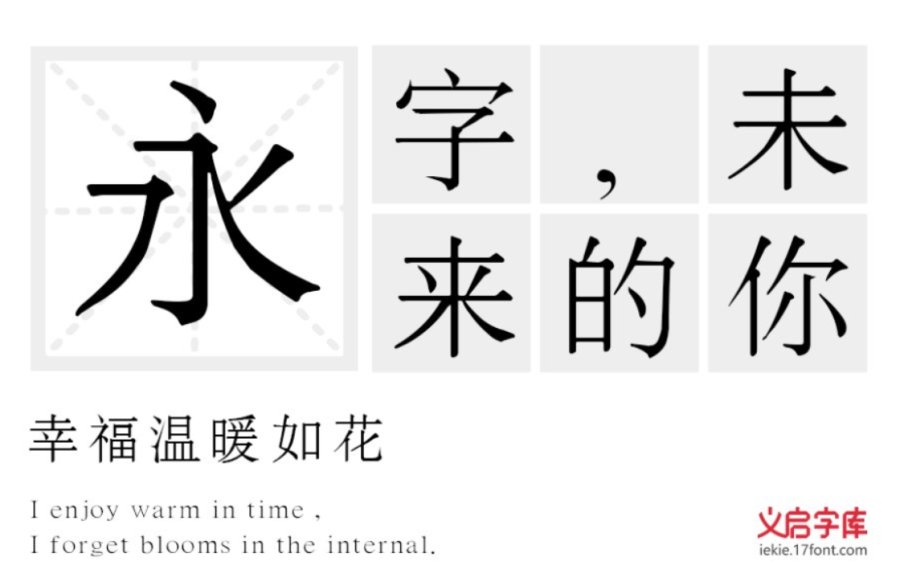
义启新宋体:这款新宋体在设计上延续了传统宋体适合印刷的风格特征,但是大大改善了在电子屏幕显示上的弊端,在比笔画上做出了细致的整改,保持比例平衡,笔画横细竖粗,字形更加清晰,适用于游戏、logo、广告、印刷等多种领域。
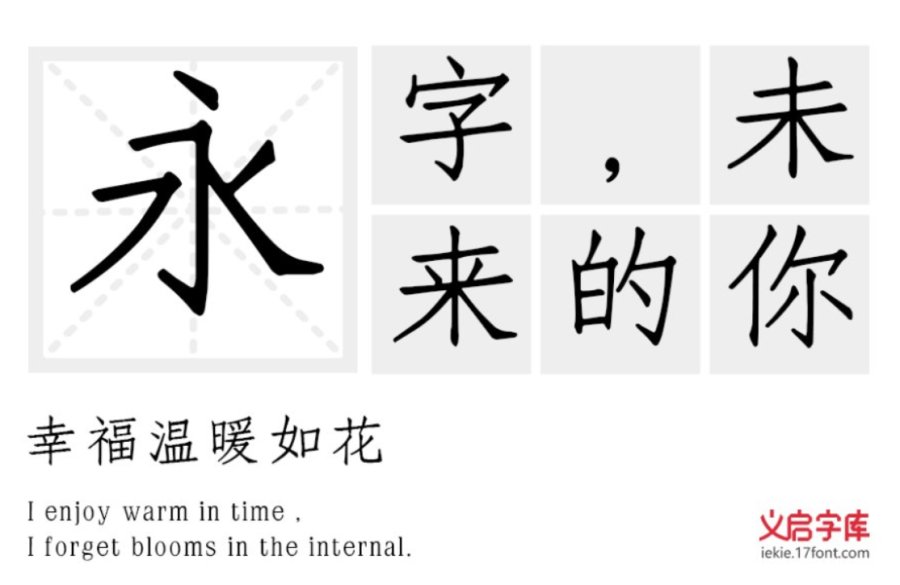
义启仿宋体:仿宋体本身其实字形更接近楷体,更加修长。笔画横竖粗细均匀,清秀挺拔,常常用作诗歌短文批注、引文等。义启的这款仿宋体气韵更加灵动,整体布局整齐又时尚。适用于logo、广告、印刷、综艺等领域都非常合适。
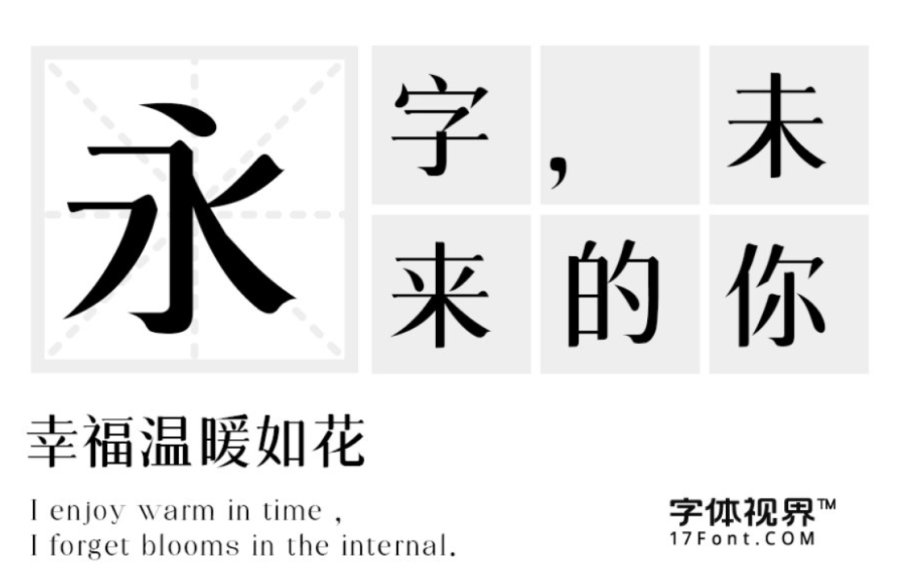
三极柔宋简体:从 字体图片 可以看出这款字体 风格清新醒目、时尚柔美,精致富有内涵。笔画的粗细反差比较大,有着强烈的视觉冲击力。个性鲜明、富有朝气。起笔收笔统一,字形清晰。